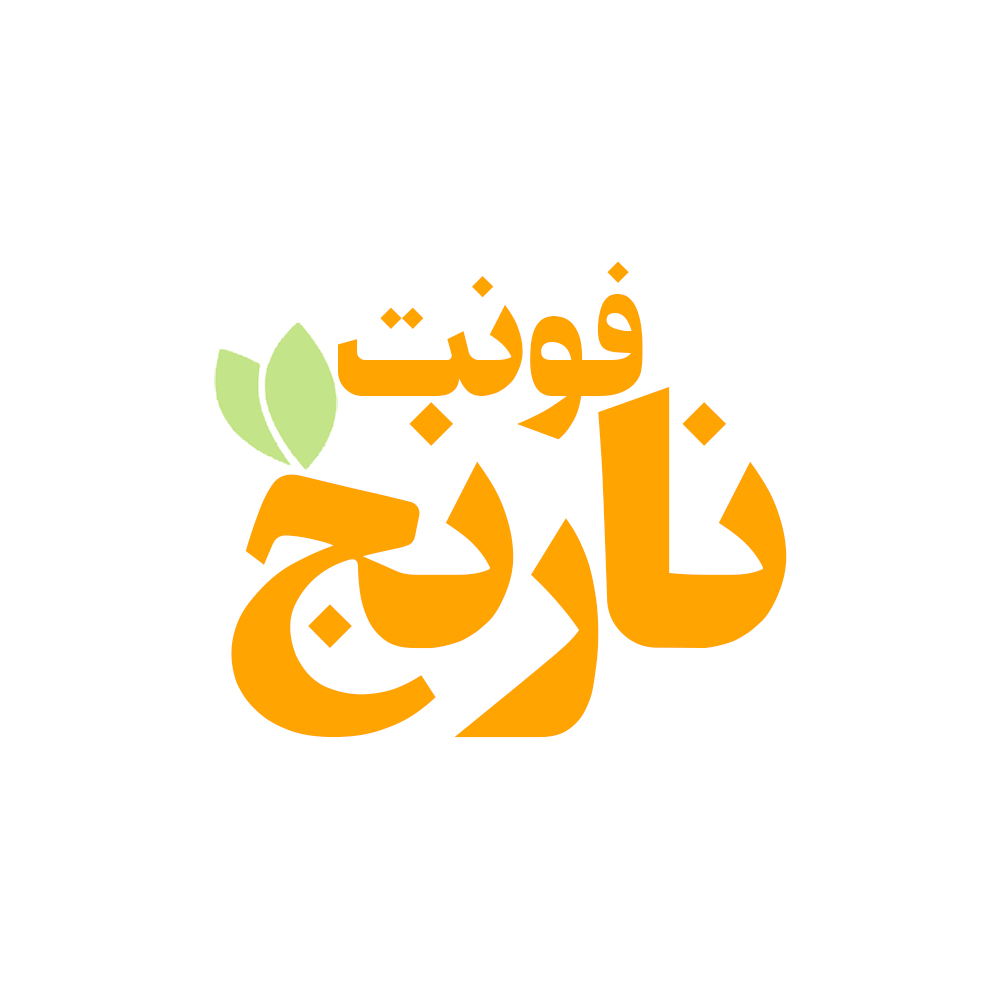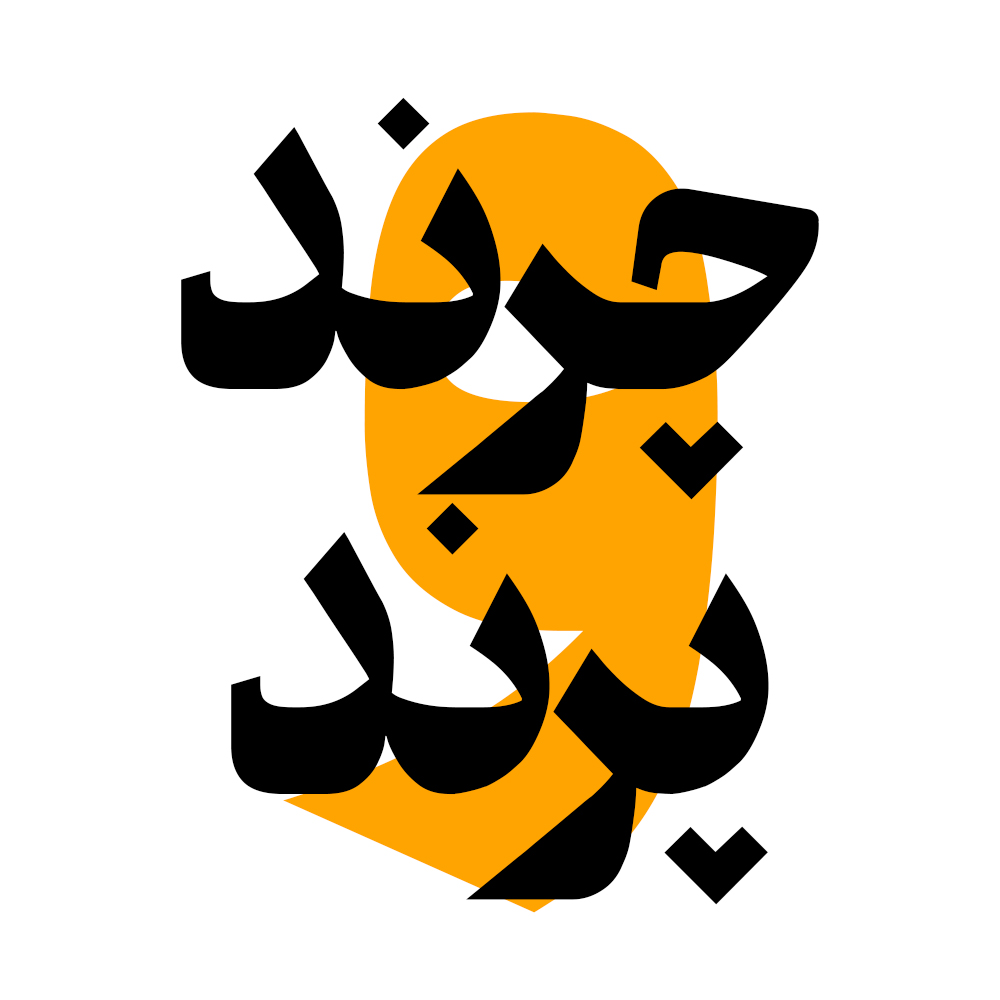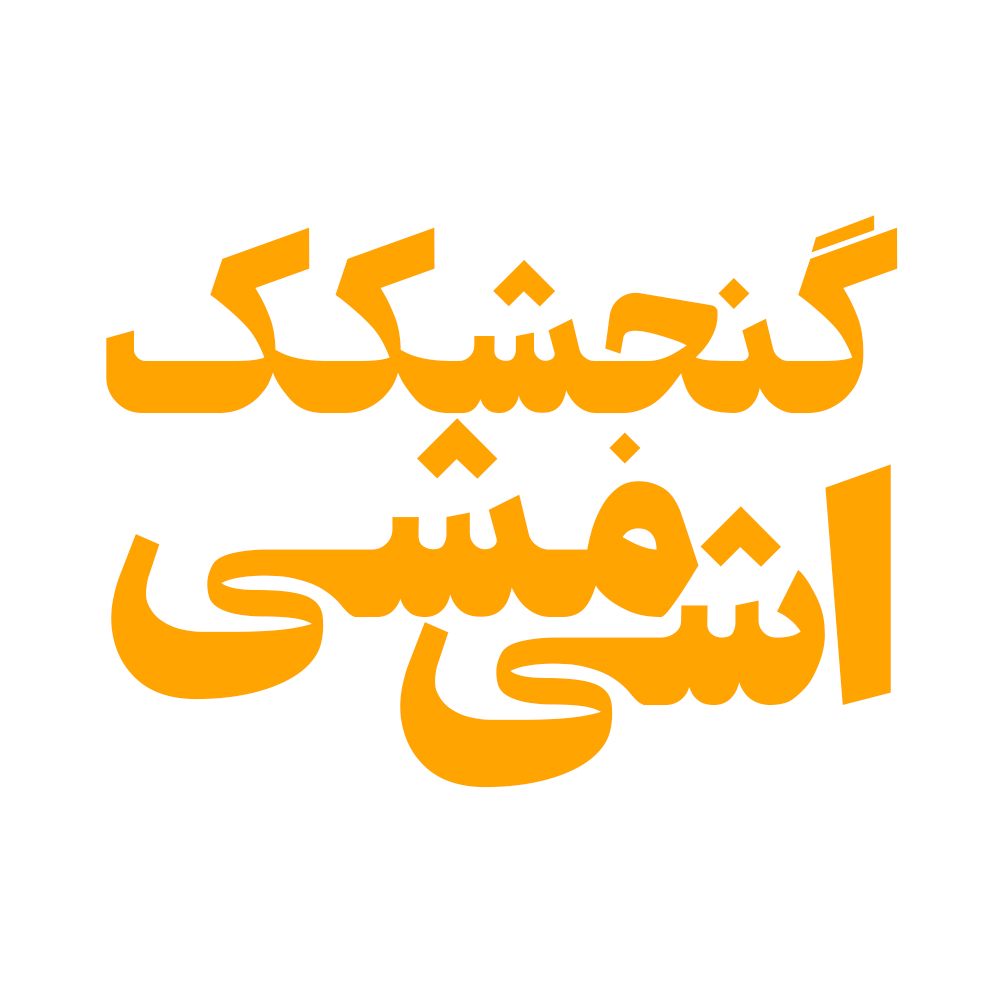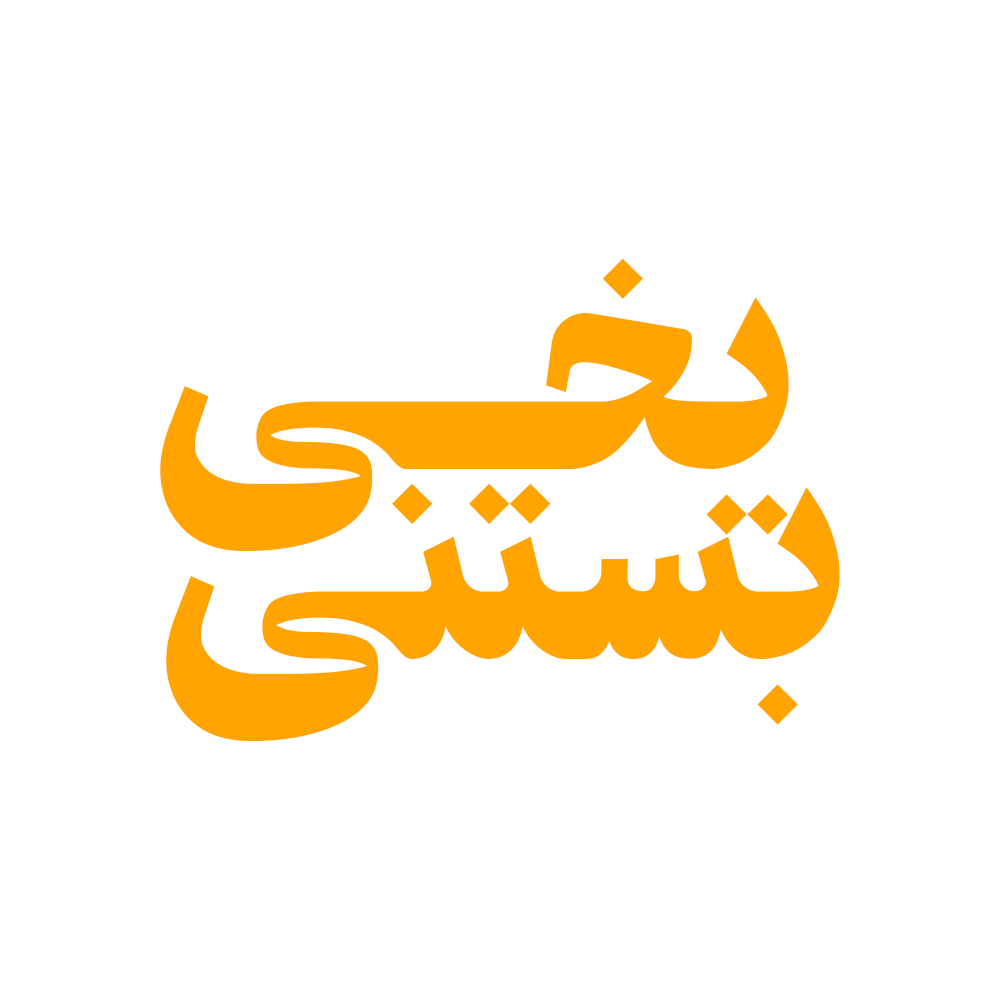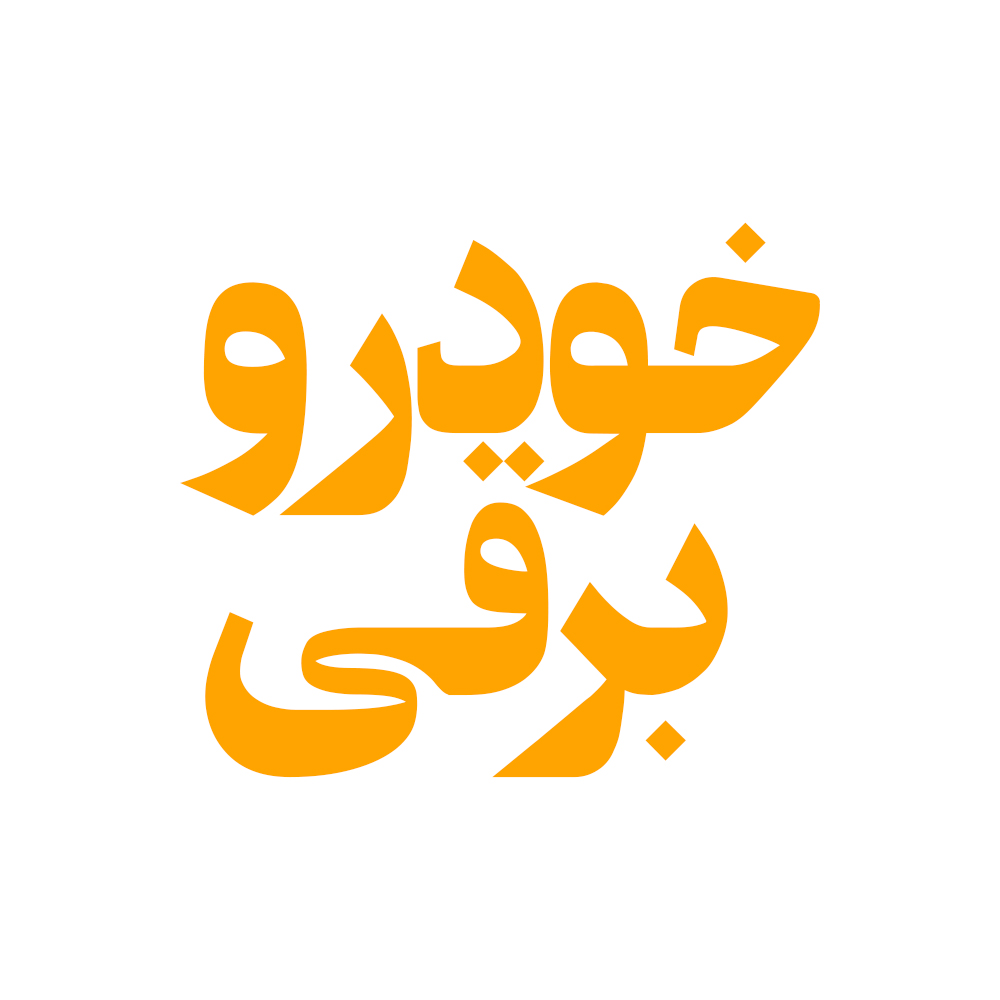
فونت فارسی نارنج Narenj Font
فونت فارسی نارنج یکی از بهترین انتخابها برای طراحی حرفهای، مدرن و منعطف هست. این فونت با ظاهر چشمنواز، ترکیب سنت و مدرنیته را به زیبایی…
فونت فارسی نارنج یکی از بهترین انتخابها برای طراحی حرفهای، مدرن و منعطف هست. این فونت با ظاهر چشمنواز، ترکیب سنت و مدرنیته را به زیبایی در خود جای داده است. در ادامه برای شما نمونه تایپ های این محصول حرفه ای رو آماده کردیم که میتونید مشاهده کنید.
پیشنمایش و نمونه تایپ های فونت نارنج